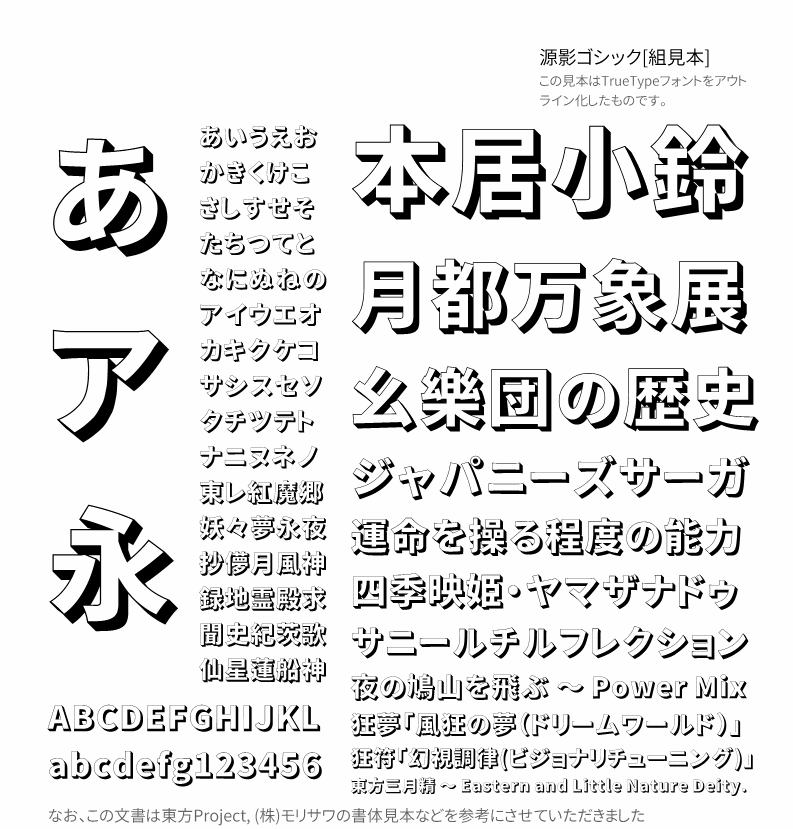
源影黑体(日文名:源影ゴシック)是基于Genshin Gothic P Heavy版本通过Fontforge软件添加的轮廓处理和阴影处理而成的字体。
制作这款字体的初衷是,在某些场景下,你很难通软件去制作字体的阴影效果,这款字体就能很好地解决阴影难添加的问题。
这个概念可能类似于森泽的“Shin Go Shadow”或 Type Lab 的“Anito Inline”。